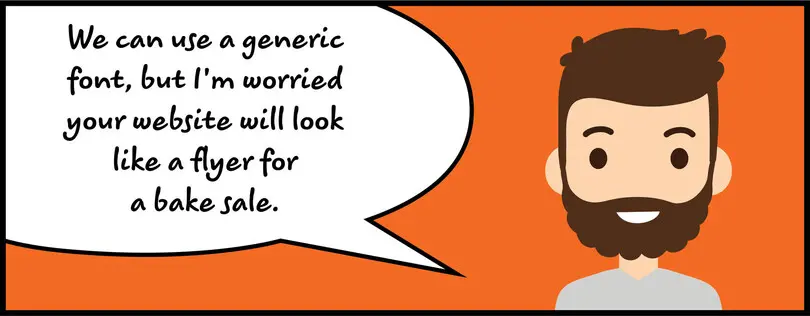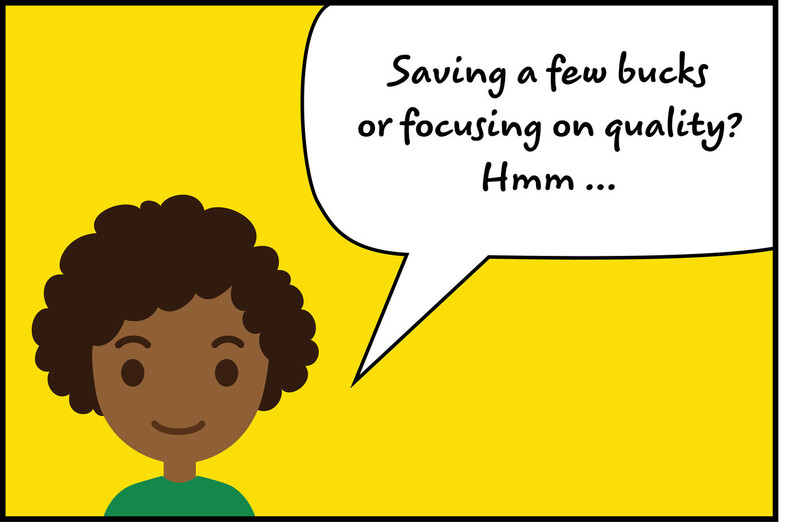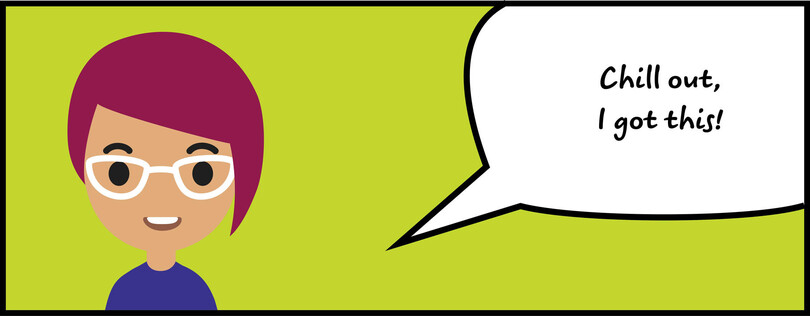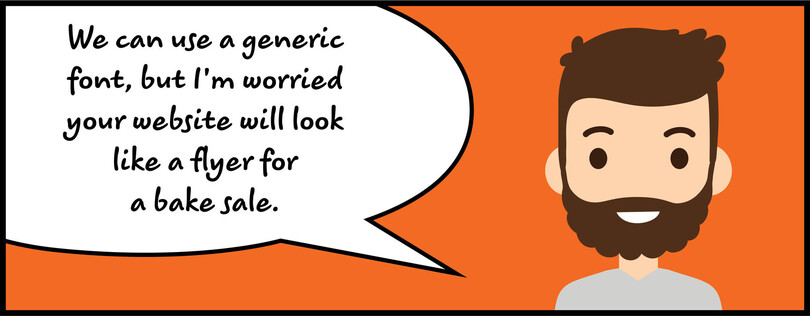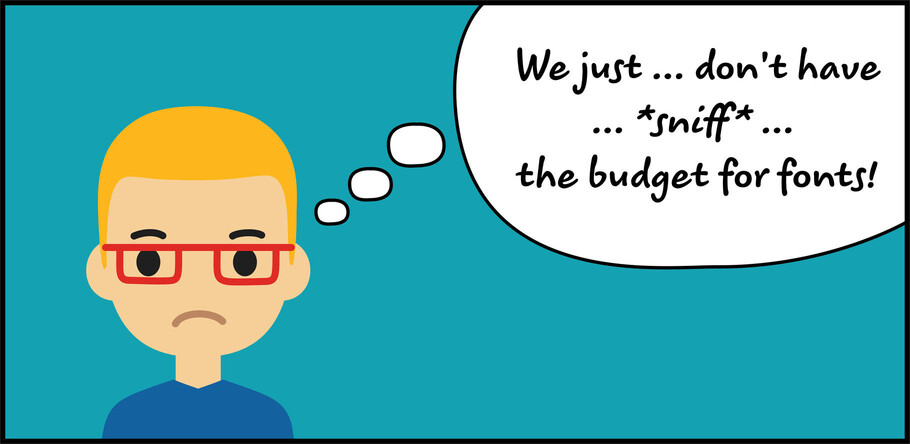
Wie und wieso Sie Kunden dazu bringen sollten, sich für Schriften zu interessieren
Sad designer thinking we just don't have the budget for fonts
Haben Sie folgenden Satz schon einmal gehört? „Schriften sind uns egal – und wo sie herkommen auch.“ Oder diesen? „Wir haben kein Geld für Schriften. Verwenden Sie einfach eine kostenlose Schrift.“
Vielleicht haben Sie zustimmend genickt. Vielleicht haben Sie aber auch mit den Augen gerollt, obwohl Sie sich sofort daran gemacht haben, das Netz nach einer kostenlosen und attraktiven Schrift zu durchsuchen. Vielleicht wollten Sie auch etwas erwidern, Sie wussten nur nicht, was, oder dachten, dass es keinen Sinn machen würde.
Dann haben wir Neuigkeiten für Sie: Es macht Sinn, und die Vorteile für Ihre Kunden und Ihr Geschäft sind bedeutend.
Kleider machen Leute – Schriften machen Unternehmen
Zunächst sei bemerkt, dass dieser Artikel nicht kostenlose oder Systemschriften heruntermachen soll. Viele kostenlose Schriften sind hochwertig und Systemschriften sind so zuverlässig wie japanische Kleinwagen. Sie haben ihren Platz im Werkzeugkasten der Designer. Doch mehr dazu später.
Saving a few Bucks
Dennoch lassen diese Optionen in Sachen Branding viel zu wünschen übrig. Kostenlose Schriften haben ihre Schattenseiten: Viele verfügen nicht über vollständige Glyphensätze, was den Fremdsprachensatz schwierig oder unmöglich macht, während bei anderen die Zahl der Schriftschnitte und Schriftgrößen begrenzt ist.
Systemschriften sind zuverlässig, aber auch allgegenwärtig. Dasselbe gilt für viele kostenlose Schriften, besonders für die hochwertigen unter ihnen. Jedermann kann sie verwenden – und tut es auch: Designer beim Gestalten von Webseiten genauso wie der Elternbeirat, wenn er den Flyer für den nächsten Flohmarkt entwirft.
Als Designer ist es Ihre Aufgabe, ein hochwertiges Design zu liefern, das vor allem Ihrem Kunden gefällt. Doch Designer können Kunden auch Möglichkeiten vorschlagen, die besser zum jeweiligen Projekt passen. Kunden verstehen vielleicht nicht, wie wichtig Schrift für einen guten ersten Eindruck ist. Ein qualitativ hochwertiges Design, das zum Projekt passt und noch dazu Lesbarkeit und Vielseitigkeit auf verschiedenen Plattformen mit sich bringt, spricht Bände über die Persönlichkeit, Glaubwürdigkeit und Detailliebe einer Marke.
Anders gesagt: Ist eine weniger geeignete Schrift, die ganz passabel funktioniert, der erste Eindruck, den Ihre Kunden hinterlassen wollen? Wohl kaum. Kunden meinen vielleicht, dass es sich nicht lohnt, für hochwertige Schriften zu zahlen, aber es ist wichtig, ihnen zu erklären, was die Folgen sein werden.
Sichere Lizenzierung
Wir hören es immer wieder sowohl von Kunden als auch von freiberuflichen Designern: Lizenzierung ist kompliziert.
Und das ist eine Tatsache. Lizenzbedingungen sind sehr unterschiedlich, und Sie fragen sich schnell, wo und wie viel eine Schrift eingesetzt werden kann, ob sie für digitale Anwendungen lizenziert ist und was Ihr Kunde gegebenenfalls tun muss, um die Lizenz weiter zu behalten. Wir sind davon ausgegangen, dass die Schrift tatsächlich lizenziert ist. Aber was, wenn nicht?
Kein Designer möchte ein Projekt mit einem Schulterzucken und einem verdrucksten „Viel Glück“ abgeben. Der Kunde läuft Gefahr, bei der Schriftnutzung rechtliche Probleme zu bekommen. Die Empfehlung von Schriften mit eindeutigen und umfassenden Lizenzen kann sich in Form von zukünftigen Aufträgen, Empfehlungen und allgemeiner Kundenzufriedenheit auszahlen.
Durch den Kauf von Schriften bei einem vertrauenswürdigen Anbieter fällt der Unsicherheitsfaktor weg. Der Lizenzumfang ist eindeutig und für gewöhnlich sind mehrere Optionen verfügbar. So können Sie Ihren Kunden leicht nachvollziehbare Optionen für Digital- und Printanwendungen vorstellen. Kunden müssen keine Schriften kaufen, um dasselbe Maß an Sicherheit zu erhalten, doch die Suche nach einzigartigen kostenlosen Schriften mit eindeutigen, umfassenden Lizenzen kann deutlich zeitraubender sein.
Weiten Sie Ihre Dienstleistungen aus
Wenn Sie Schriften und die Mechanismen der Schriftenlizenzierung verstehen, können Sie Ihren Kunden einen Mehrwert bieten. Dieses Fachwissen gibt Ihnen einen Wettbewerbsvorteil gegenüber anderen Designern und kann zu deutlich mehr Mundpropaganda führen.
Sie können sich so auch auf verschiedene Arten vermarkten. Neben Ihren Talenten als Designer verfügen Sie auch über Ideen und Lösungen, die Sie Marken über den Umfang des laufenden Projekts hinaus empfehlen können. Kunden freuen sich, wenn ein Designer sie zu den ästhetischen und Branding-Vorteilen von Schriften beraten und gleichzeitig potenzielle rechtliche Stolpersteine aus dem Weg räumen kann.
Chill Out
So können Sie im Kundengespräch punkten und sich auch langfristig Aufträge sichern. Ihr Dienstleistungsangebot zeigt einen talentierten Designer, der über den Tellerrand hinausschaut und Probleme für Marken löst. Und das freut potenzielle Kunden immer.
Dennoch ist es wichtig, dieses Gespräch zu führen. Viele Kunden kennen die Möglichkeiten noch nicht. Ein wenig mehr Informationen über Schriften und ein vorsichtiges Anstupsen kann auch bei Kunden, die auf eine kostenlose Schrift bestehen, einen bleibenden Eindruck machen. Wie das Gespräch auch ausgeht: Sie stehen als Schriftkoryphäe da – und das kann Ihnen beim Aufbau Ihres Rufs und bei der Erweiterung Ihres Fachwissens nur helfen.
Font in den Sprechblasen: FF Uberhand, Jens Kutilek (2017)